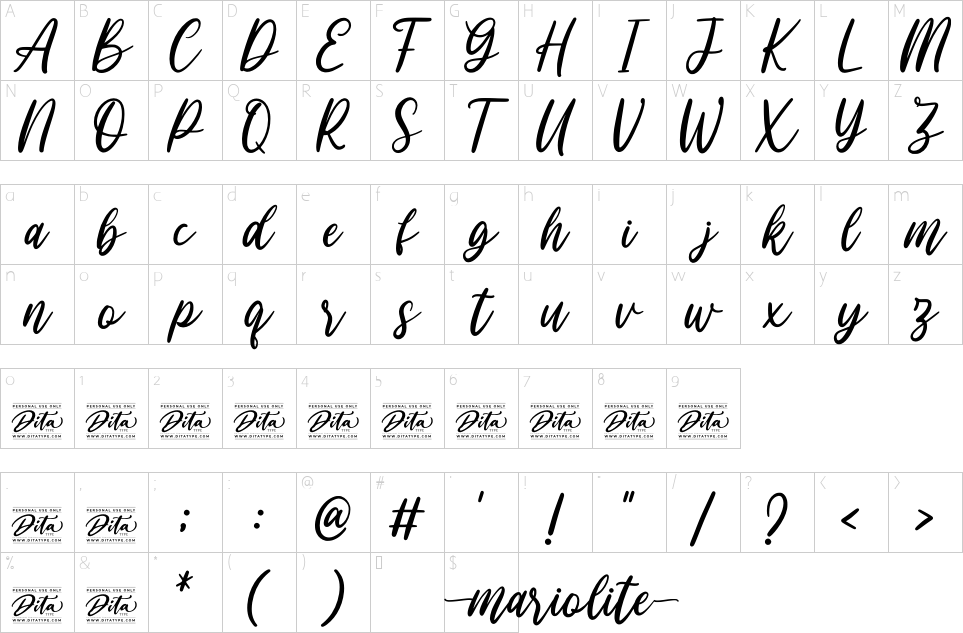
Descubra Mariolite, uma fonte de graça disponível para Windows e Mac. Desenvolvida pelo designer Dita Type, Mariolite é uma escolha perfeita para designers gráficos em busca de uma fonte atraente e versátil. Essa fonte foi projetada para ajudar a personalizar seus projetos digitais de maneira única e harmoniosa. Com mais de 3.179 downloads, Mariolite já foi usada por designers de todo o mundo para adicionar um toque único e elegante a seus trabalhos. Seja para criar gráficos de e-mail, artigos, design gráfico ou até mesmo para personalizar sua identidade visual, Mariolite é uma ótima opção para quem procura um visual moderno e moderno. Não perca tempo, descubra agora Mariolite e personalize seus projetos de design digital.